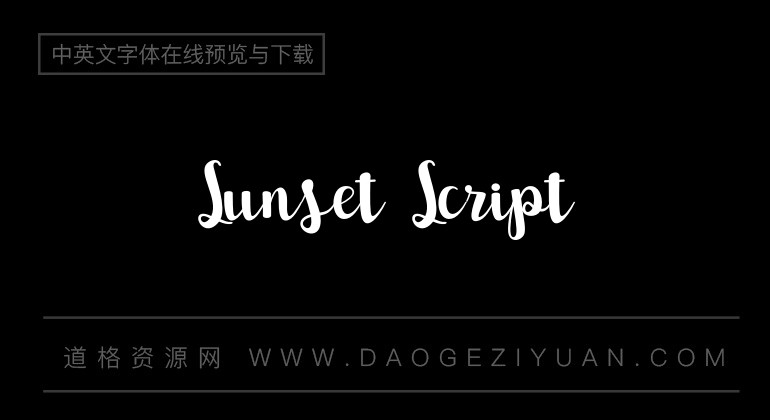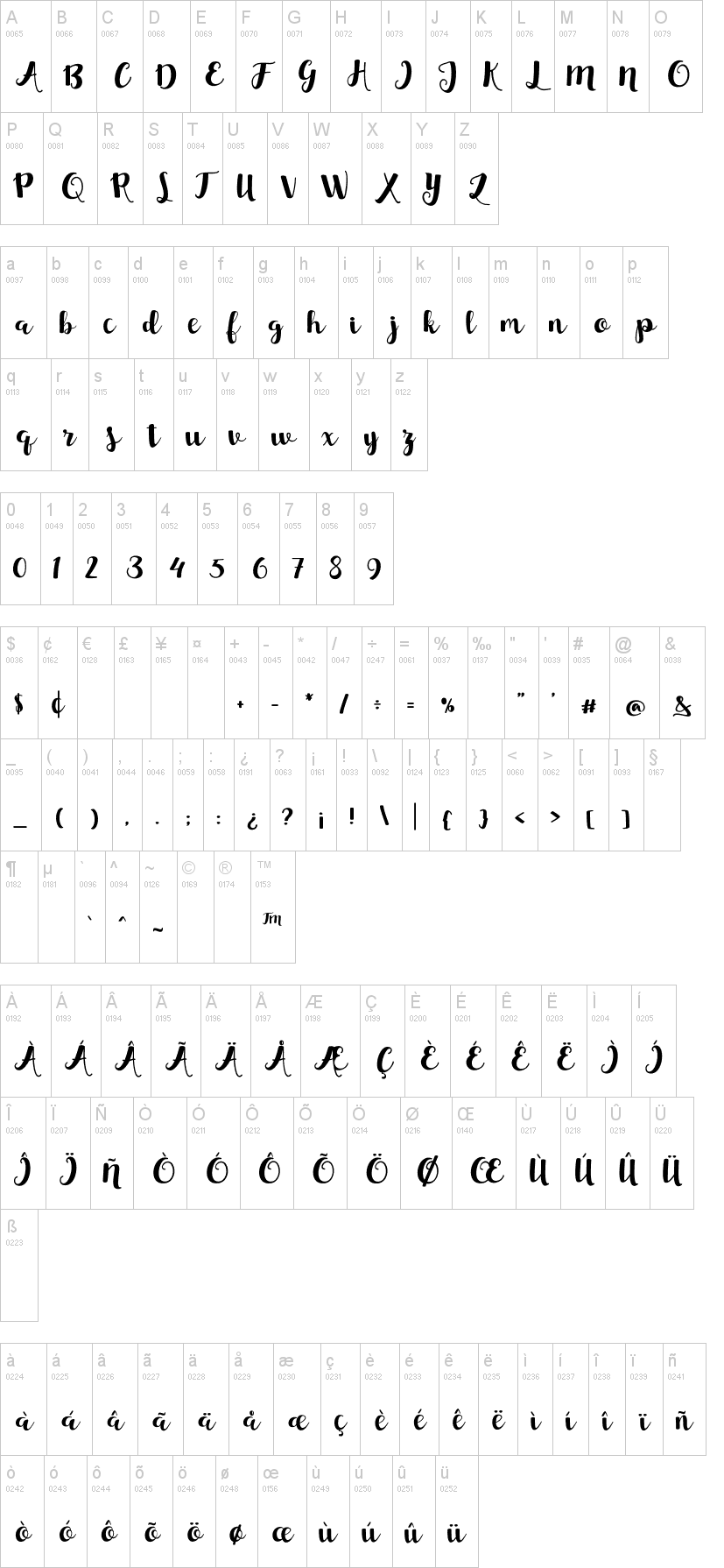
? Sunset Script 是一款由 Fontfabric 公司设计的脚本字体,它具有流畅的线条,灵活的设计和精致的细节,可以为您的设计带来活力和活力。它具有多种字体,包括附带的拉丁文字母,带有欧洲字符和绘图符号的多种字体,以及可以定制的字体,可以满足您的所有需求。它可以用于创建多种形式的设计,包括海报,标志,标题,报纸文章,书籍封面,网页设计等等,可以满足您的各种设计需求。内容介绍
Sunset Script是一款非常不错的手写艺术字体,具有很好的视觉感,适合于文化类的宣传设计、商业类品牌的广告和产品包装设计以及个性化文字排版等较多场景。